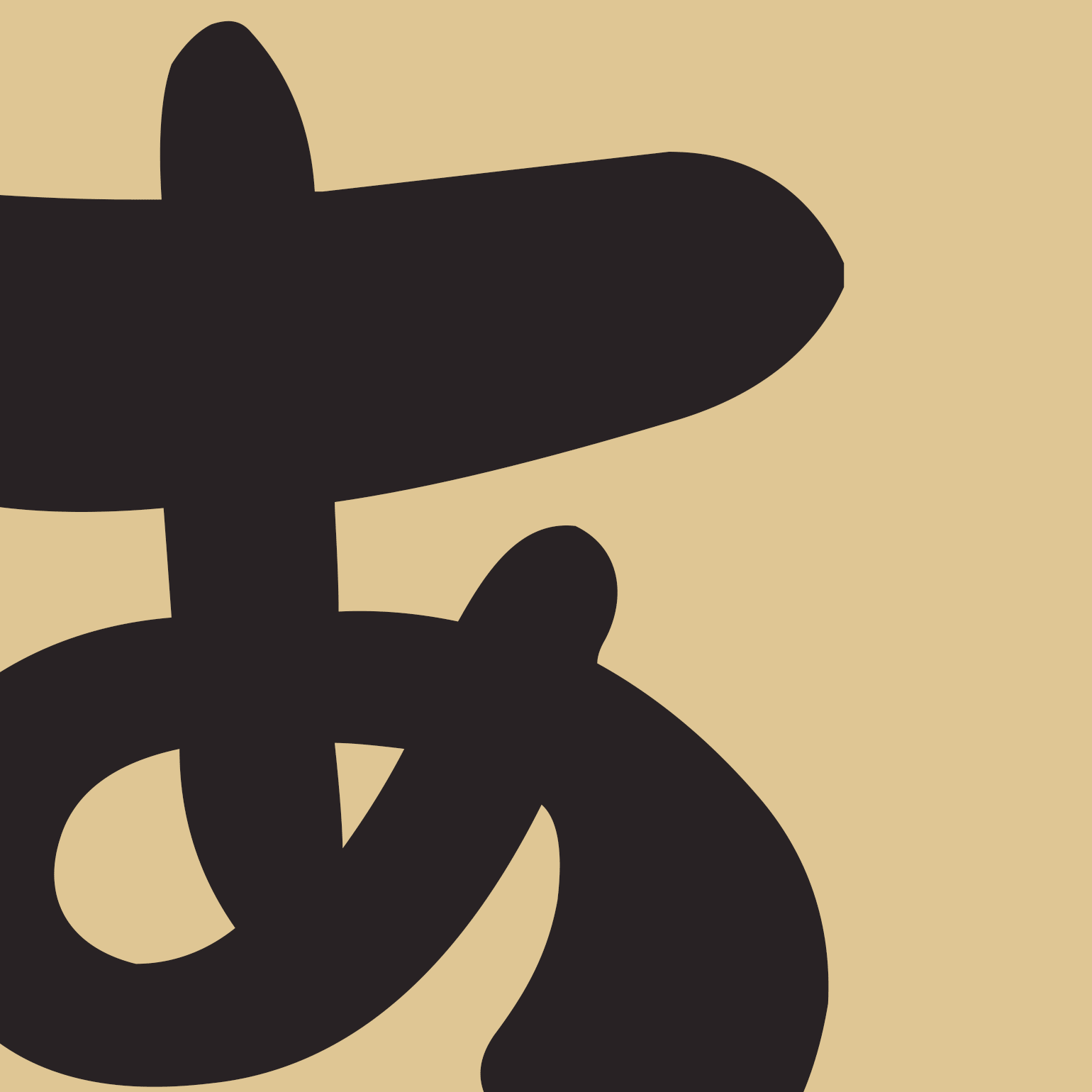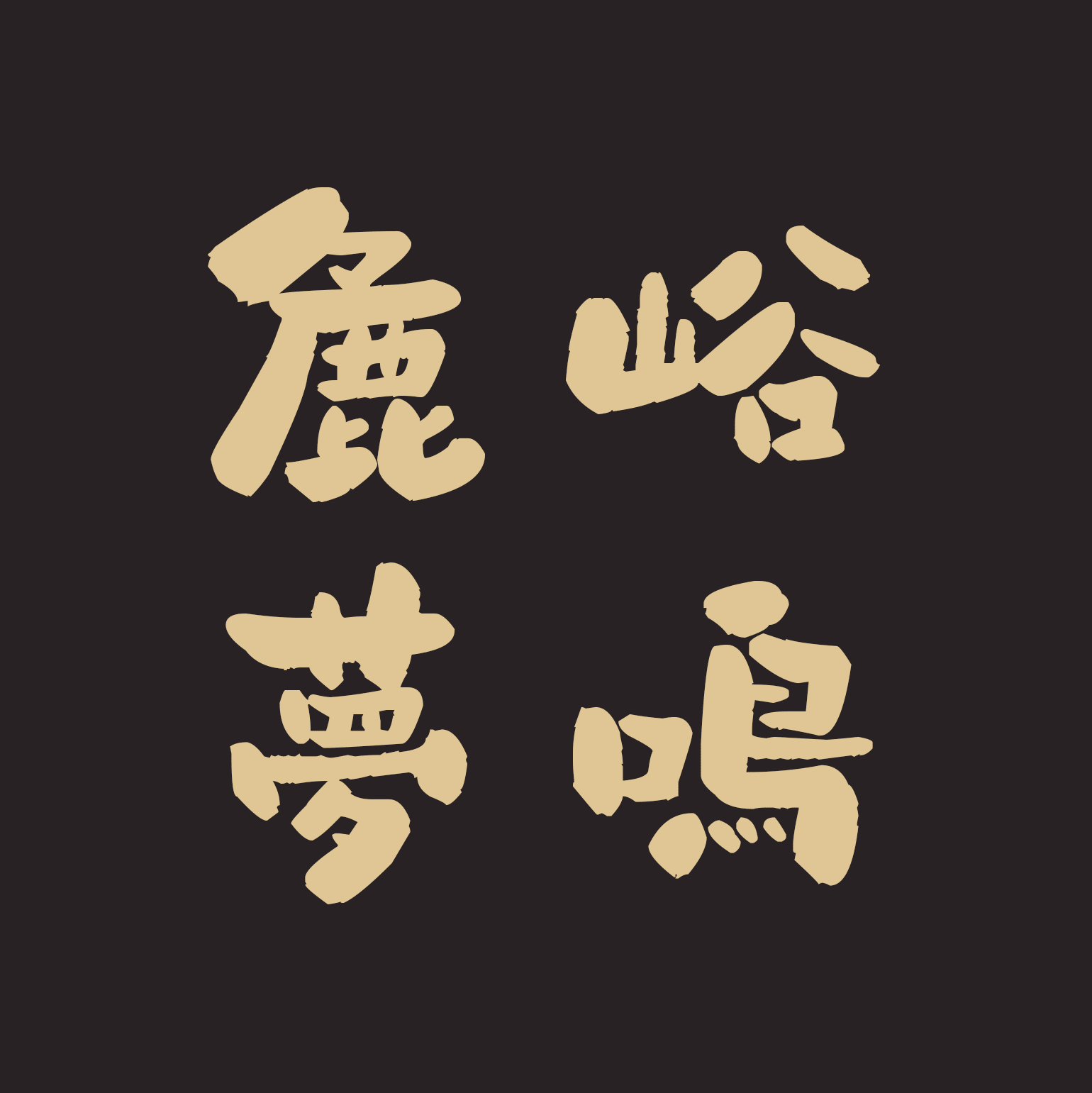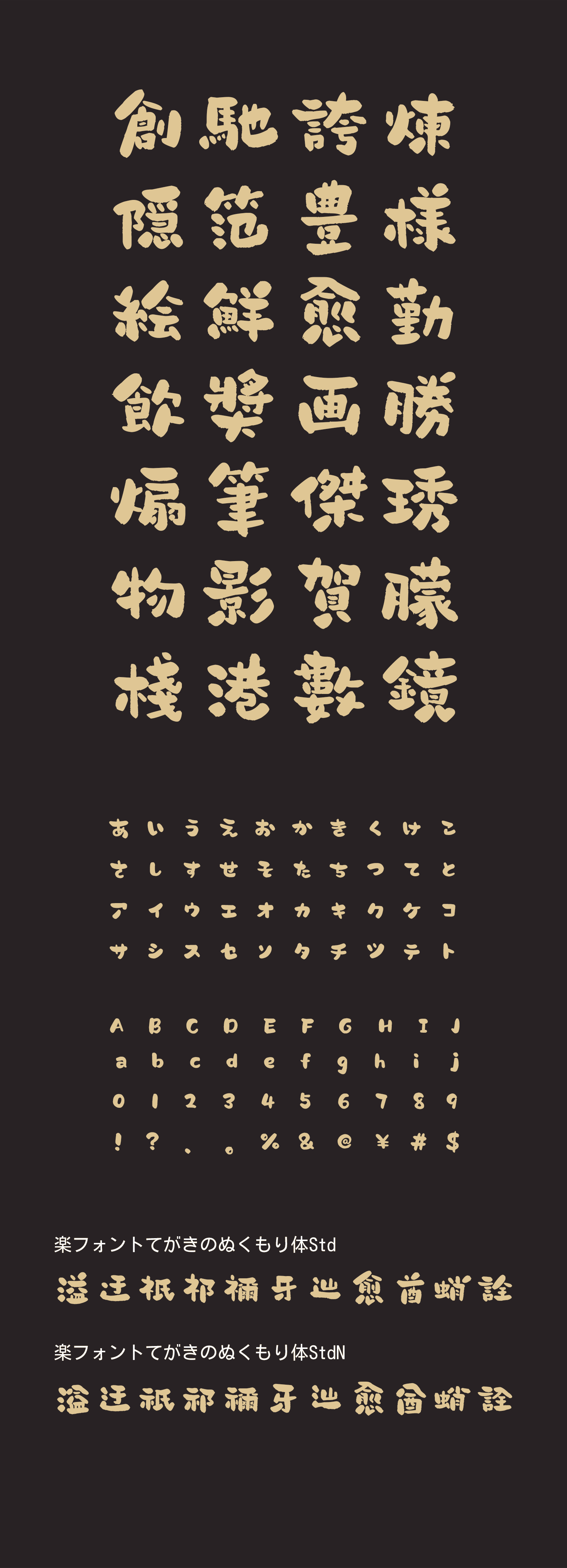
てがきのぬくもり体(てがきのぬくもりたい)
楽フォント
てがきのぬくもり体(てがきのぬくもりたい)
筆致の太さに変化があり、巧みさを素朴さに隠しつつ、抑揚のあるデザインが特徴です。筆画の絶妙な切れ間が、軽やかさと自由さを演出しています。全体のスタイルは剛と柔を兼ね備え、柔軟でありながらも素朴で重厚な印象を持ち、豊かな奥行きを感じさせます。